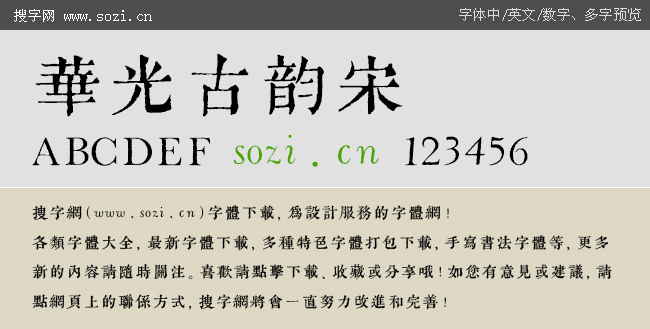
華光古韻宋
搜字網(wǎng)給大家提供一款華光古韻宋中文字體下載,華光古韻宋取材自清代嘉慶年間《湖海樓叢書》中的刻本字體,在保留原刻本形韻的基礎(chǔ)上,設(shè)計完成漢字字符7113字,以滿足日常用字需求。字形清秀挺拔,結(jié)構(gòu)穩(wěn)重,筆形橫細(xì)豎粗,撇長而精,捺粗而拙,體現(xiàn)出古拙感和文藝感、雕刻感。通過優(yōu)化字形結(jié)構(gòu)及筆形,使辨識度得到了加強。為展現(xiàn)出古樸的風(fēng)格,全套字庫為繁體字形。適合應(yīng)用于藝術(shù)設(shè)計、平面宣傳設(shè)計、網(wǎng)頁設(shè)計、海報設(shè)計等應(yīng)用。